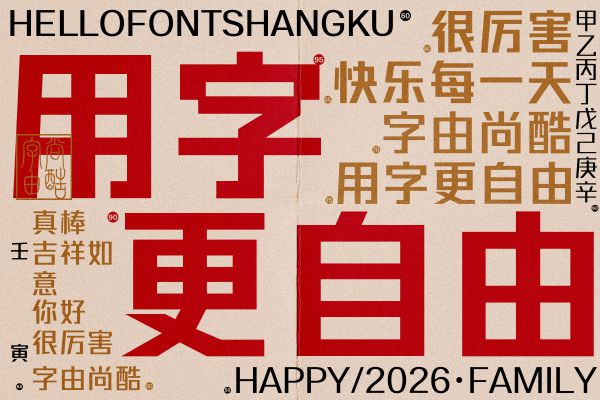
汉仪粗简黑繁
为了满足当今跨媒体时代对于中文字体显示功能和美学功能的高品质要求而量身打造的全媒体中文字体。 字体设计理念:简黑在设计中以汉仪字库中的经典黑体作为基础和依据,在其基础上进行系统优化,扬长避短。现在看来,黑体上的“喇叭口”不仅是配合传统印刷技术条件下的中文字体设计解决方案,也是中文字体历史性和时代性的标签,简黑对于传统黑体中的“喇叭口”进行了功能性的整理,在使得字体能够在各种不同要求的媒体上显示都能够有清晰疏朗的优质表现的同时,更带来符合现代字体审美需求的:精致、简约、清透、自然的视觉感受;简黑追求最佳字面效果,字体的字面是直接影响排版效果和阅读感受的重要因素,因此简黑在设计之初针对于早期黑体字面过小和时下流行的大字面字体进行了系统梳理和研讨,针对于理想的字面展开了一系列的分析和调研,从而希望能够实现更加科学化和人性化的字面空间;中西文完美配搭是简黑的一个亮点,精心设计的西文、数字及符号不仅追求风格气质的和谐统一,更加着重于打造中在实际应用版面中中西文、数字及符号的全面配合的。 简黑的系列化开发,一方面是将其精致、简约的特点和优势通过粗细变化充分展现出来,另一方面是基于字形结构稳定性的考量,有效避免了用户自行排版操作造成字体丧失原本特性的风险,从而使简黑家族可以满足不同用户的各种不同需求,扩大了简黑的市场,功能性也更加强大。